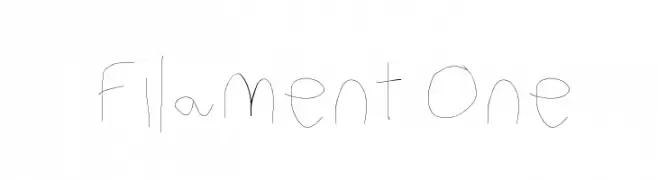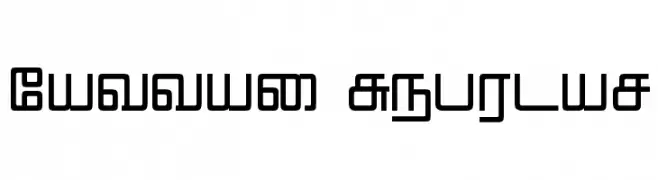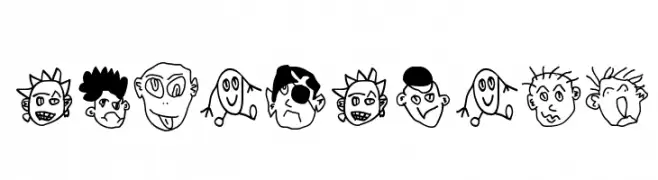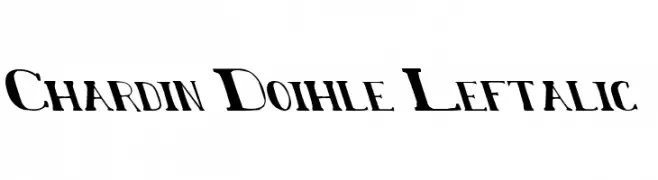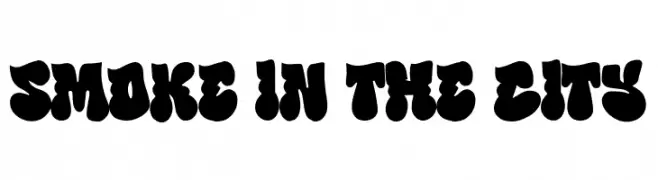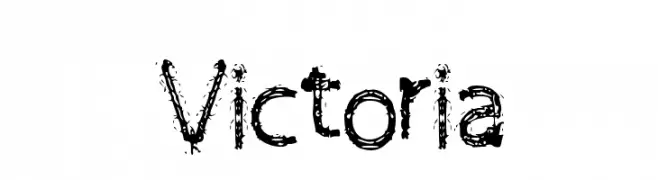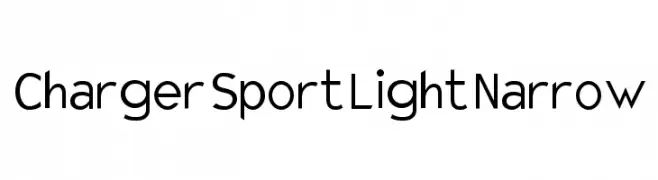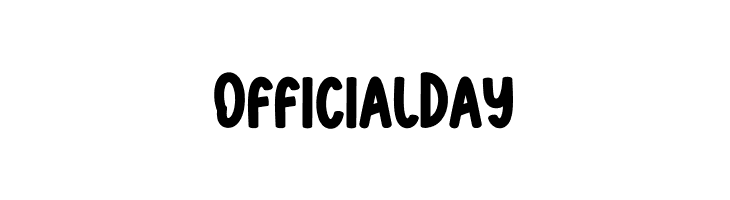
Добро пожаловать в раздел Топ шрифтов — здесь популярность встречается с качеством. Это самые скачиваемые и используемые шрифты нашего сообщества за этот год. Если нужны надежные варианты для логотипов, сайтов или соцсетей — начните отсюда.
Каждый топ‑шрифт отличается балансом, читабельностью и универсальностью. Здесь есть современные гротески, изящные скрипты, винтажные антиквы и минималистичные дисплейные семейства. Если не знаете, с чего начать, раздел «Топ» — ваш короткий путь к проверенной типографике.
A delicate, hand-drawn font with thin, whimsical strokes and an organic feel.
Cartoonish, hand-drawn font made of expressive human head illustrations.
A bold, left-slanted font with high contrast and distinctive serifs.
Bold, playful font with a bubbly appearance.
A bold, distressed font with a vintage, industrial style.
A bold, high-contrast serif font with dramatic strokes and sharp serifs.
A bold, distressed font with a hand-drawn, textured appearance.
Какие шрифты в топе прямо сейчас?
Дизайнеры любят Filament One, Nattai Regular, HumanHeads, Chardin Doihle Leftalic and Smoke in the City за чистые формы и широкий спектр применения — от фирменного стиля до лендингов и постеров.